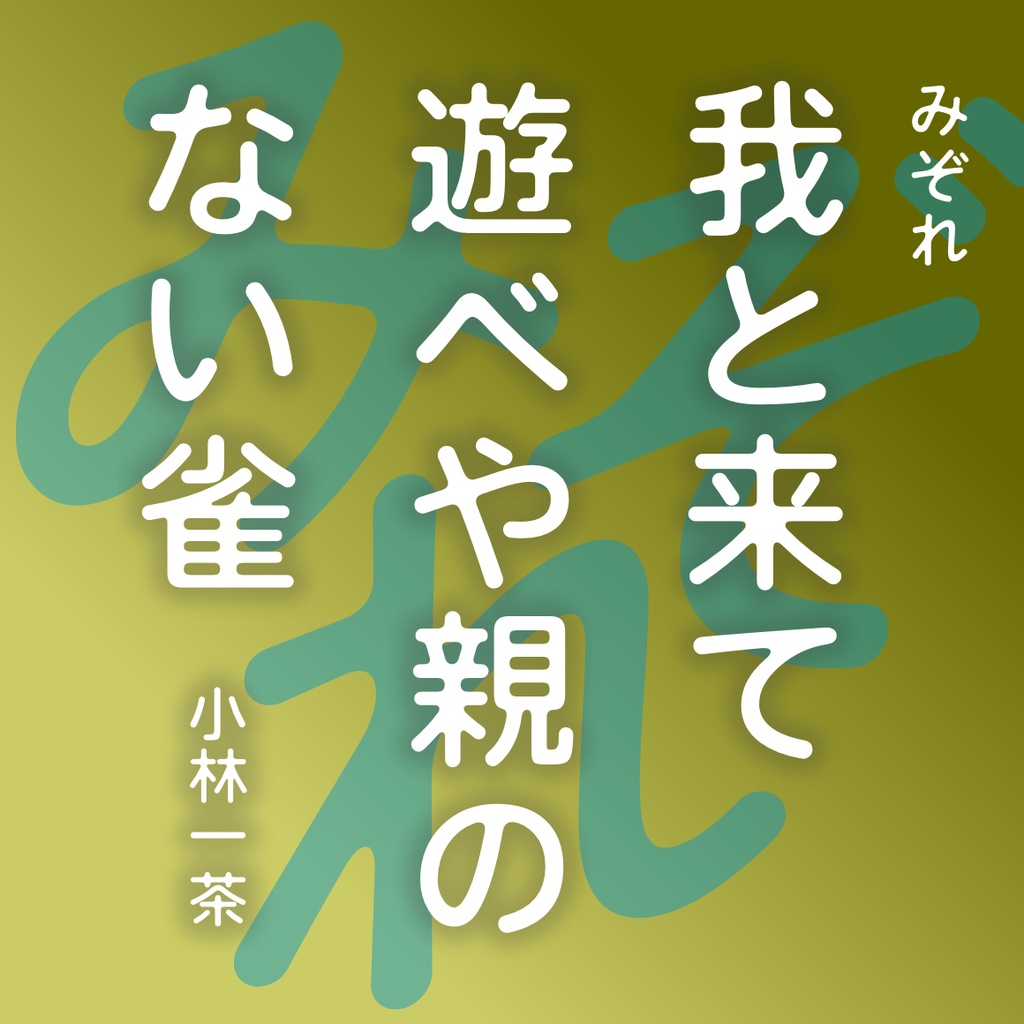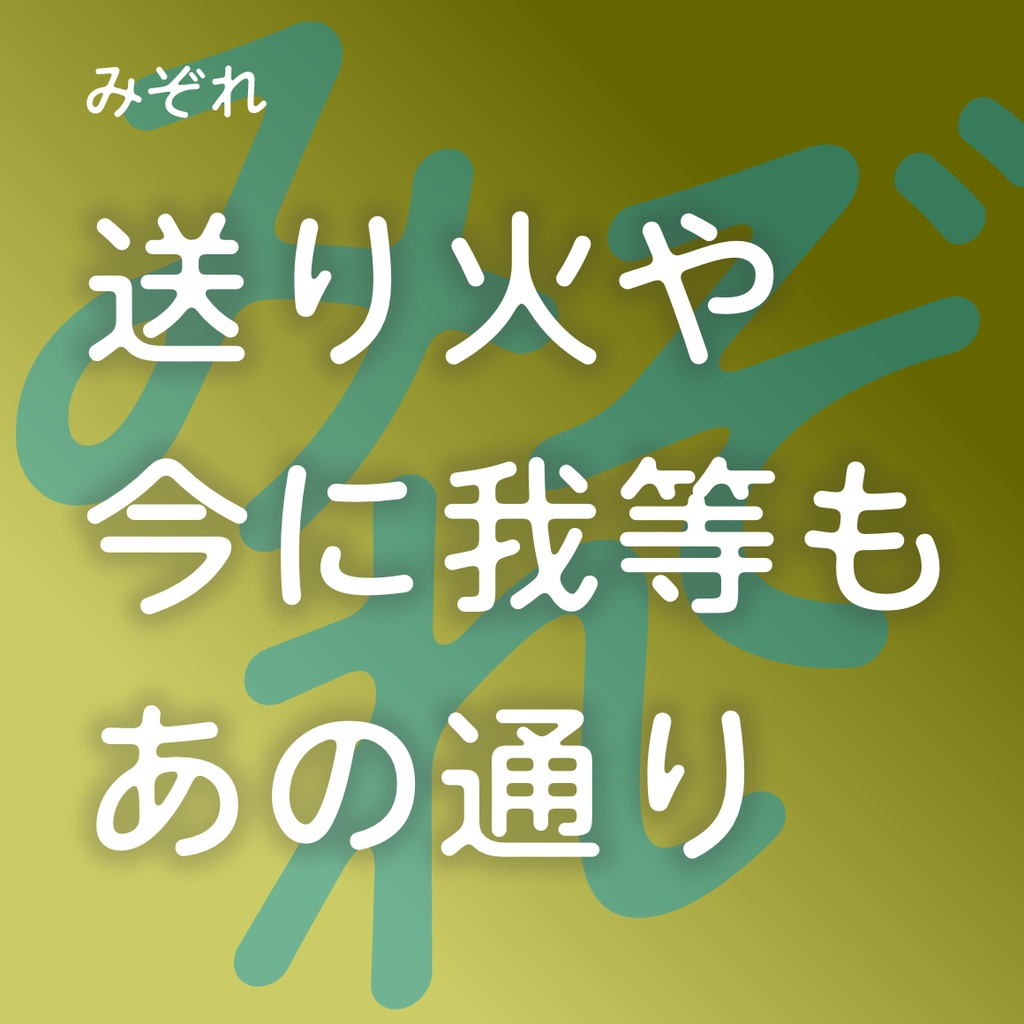
丸ゴシックのレラ-4をベースに、新しく開発した日本語フォントです。
線画の交点に丸みを与えた、日本独特の情感(潤い・温もり…etc.)たっぷりのデザイン。
あなたの言葉や想いが、相手の心に優しく伝わる柔らかい表情のフォントです。
いちおう見出し用として制作しましたが、本文に使っても言葉が柔らかく伝わる気がします。